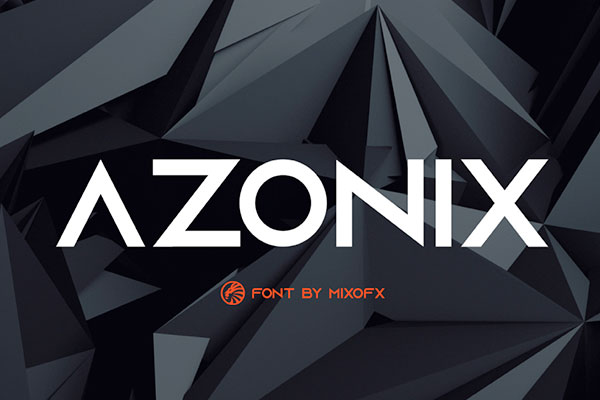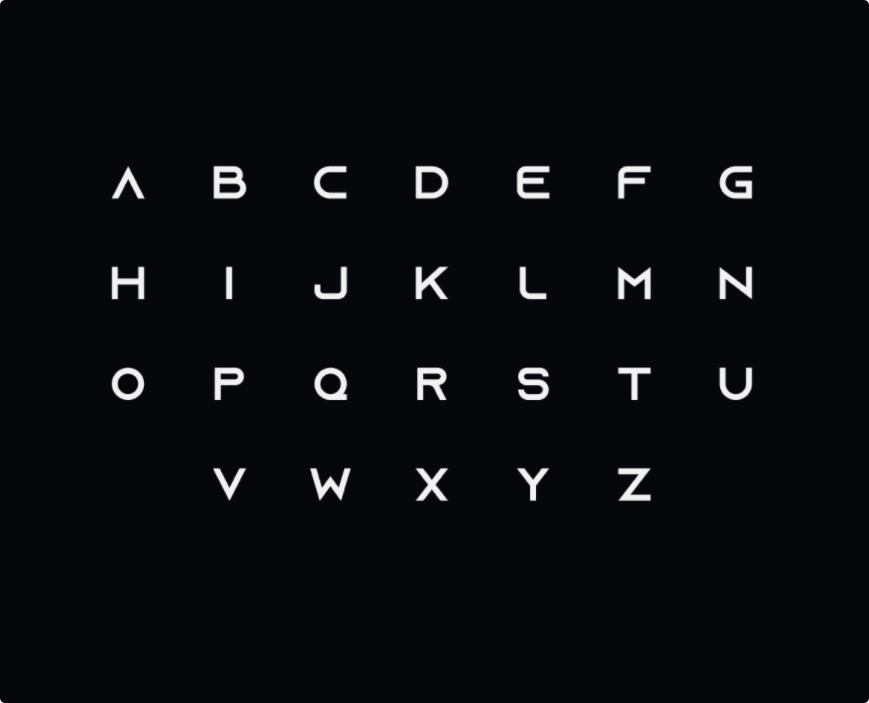
Azonix字体
Azonix是一款由国外设计师MixoFX创作的英文字体,以其简约现代的无衬线风格深受欢迎。这款字体独特之处在于其大胆的几何大写字母、数字和标点符号,充满了形式美感。
Azonix字体的设计注重简洁和现代感,去繁就简,展现出几何线条的独特魅力。这种字体适用于各种设计和商业场合,如海报设计、宣传物品、广告标语等。
Azonix效果预览
Azonix字体效果预览